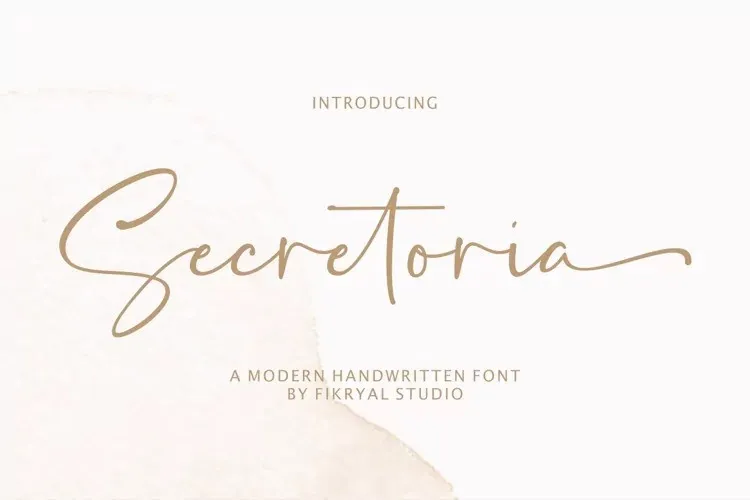
“Descubra uma nova joia para suas criações digitais com a Secretoria Font – uma tipografia de calligrafia romântica e doce criada no estilo moderno, com terminações suaves nos começos e fins das linhas. Perfeita para seu design geral, esta fonte casual se destaca para logotipos, marcas, títulos, posts nas mídias sociais, anúncios, embalagens de produtos, designs dos produtos, rótulos, fotografia, marca d’água, eventos especiais, revistas, design da web e muito mais. Experimente o charme único desta tipografia elegante e experimente criar algo verdadeiramente único no seu próximo projeto.”